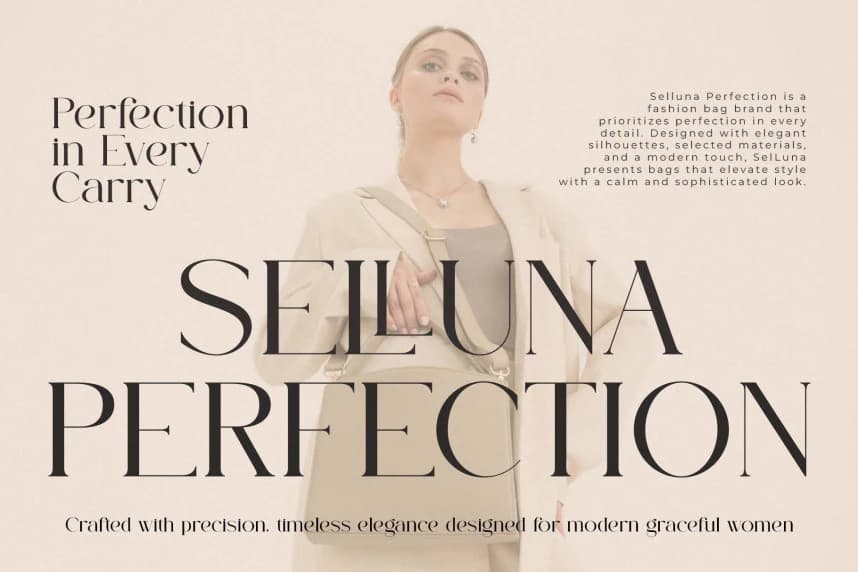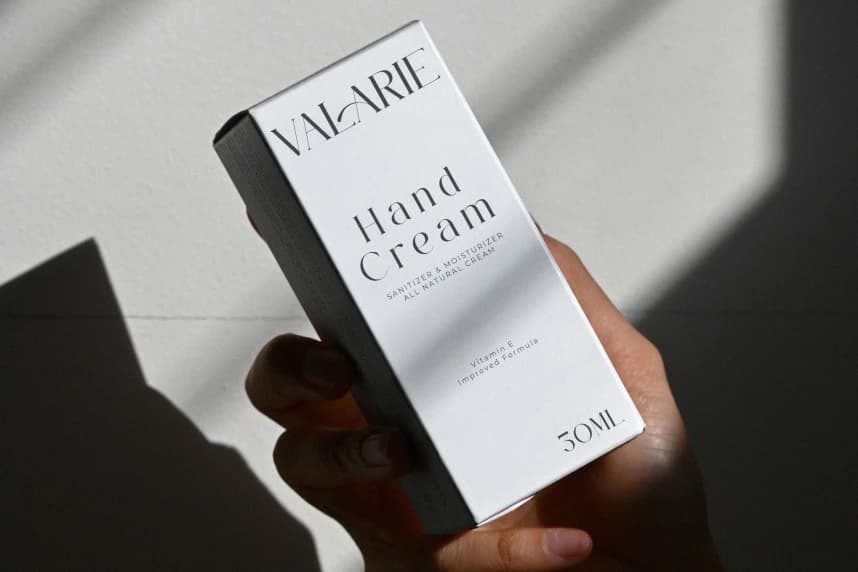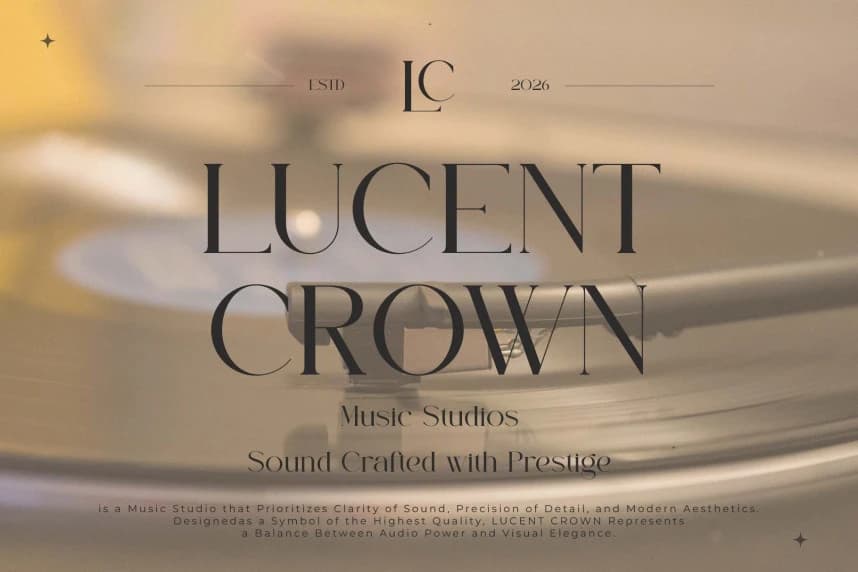
Michty Yazı Tipi
Michty Font: zarif, güzel ve modern bir Serif. Modern ve minimalist görünümüyle Michty, web siteleri, modern logolar, marka kimlikleri, sosyal medya alıntıları, düğün kırtasiye ürünleri, dergiler ve daha fazlası gibi projelerinize lüks, şık ve temiz bir stil kazandırır!
Michty Font zarif, güzel ve modern bir Serif'tir. Modern ve minimalist görünümüyle Michty, web siteleri, modern logolar, marka kimlikleri, sosyal medya alıntıları, düğün kırtasiye ürünleri, dergiler ve daha fazlası gibi projelerinize lüks, şık ve temiz bir stil katıyor!